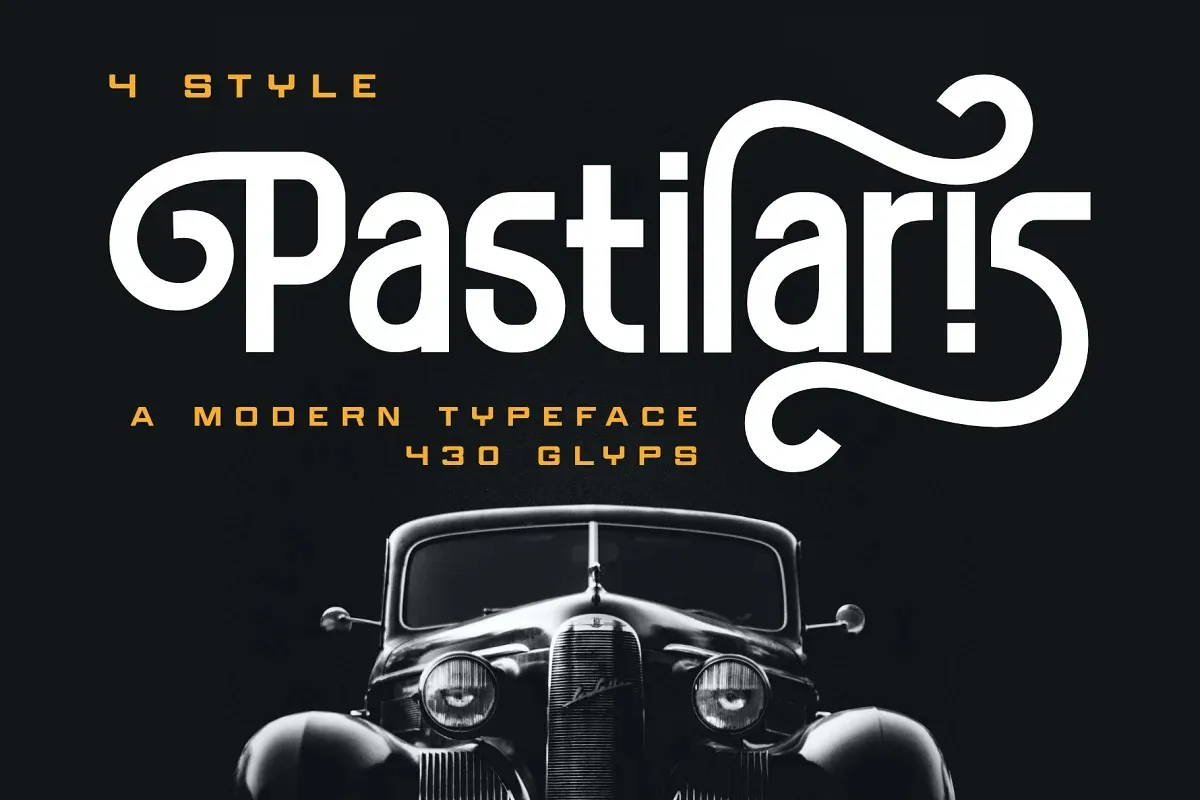
A fonte “Pastilaris Font” é uma elegante tipografia sans-serif que traz uma nova dimensão ao seu projeto visual. Fabricada pela Dumadistyle, essa fonte oferece um amplo leque de 430 caracteres únicos e variáveis, garantindo que você tenha infinitas opções para personalizar sua projeção de maneira única e sofisticada. A Pastilaris Font é perfeita tanto para projetos gráficos quanto para design web, sendo ideal para adicionar um toque moderno a qualquer layout ou aplicação digital. Ela oferece uma escolha vasta que vai desde linhas sutis até estilos mais marcantes, tudo isso em uma tipografia sans-serif limpa e moderna que certamente irá enriquecer seu design.